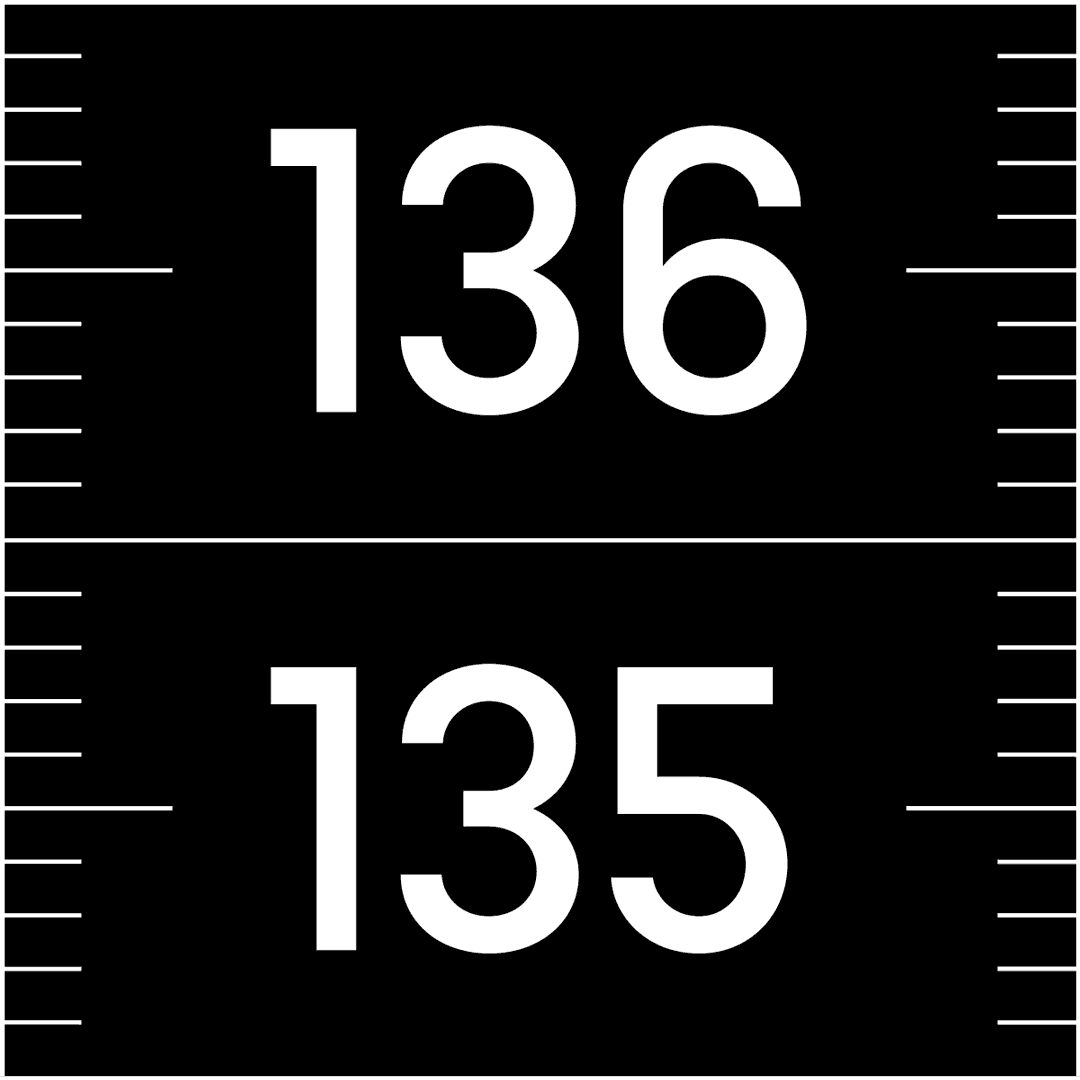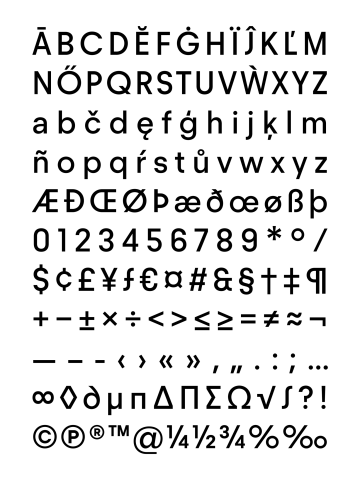
Pietro
Geometrický grotesk Pietro vzniknul v roce 2019 jako součást omlazení české oděvní značky Pietro Filipi. Podobně jako její nové logo ho formoval současný důraz na digitální komunikaci a potřebnou flexibilitu v tisku a online. Písmo v jednom řezu základní tmavosti tak představuje současný pohled na žánr, jehož nejznámějším zástupcem je pravděpodobně Futura Paula Rennera. Balancuje mezi klasickými proporcemi, geometrickou přísností a funkčností a univerzální přitažlivost jeho neutrální kresby mu dodává udržitelnou nadčasovost. Znaková sada obsahuje minusky a verzálky v široké jazykové podpoře.